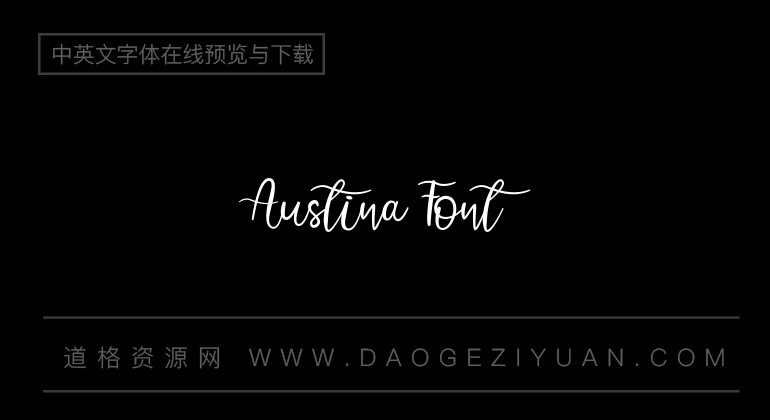
Austina是一种优美的手写字体,由美国设计师 Emily Spadoni 创作。该字体在2015年发布,并在许多不同的设计项目中得到了广泛应用。 Austina字体具有优美、流畅、灵活和优雅的特点,其字形充满了个性和韵律感。它的笔划和弯曲形状使得这种字体看起来非常柔和和温暖,适合用于众多的设计项目,如书籍、海报、名片、包装等等。它还有许多可用的字重和风格,像常规、粗体、斜体等,可在不同情况下使用。 总的来说,Austina Font 是一种优美的手写字体,适用于许多设计项目,可以带来独特的感觉和个性。内容介绍
Austina Font是一款非常不错的手写艺术字体,具有很好的视觉感,适合于文化类的宣传设计、商业类品牌的广告和产品包装设计以及个性化文字排版等较多场景。